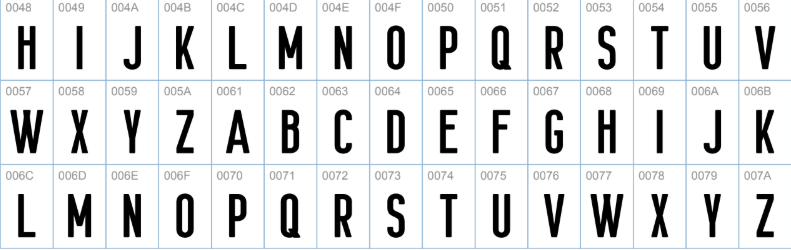
Essa mudança de fornecedor impacta drasticamente a identidade visual do kit. Saem as fontes clássicas e serifadas, entra uma tipografia moderna e agressiva. Neste post, você baixa a fonte oficial exata desta nova fase, pronta para estampar seus projetos.
- Conteúdo: Alfabeto completo (Caixa Alta) e numeração oficial da temporada 26.
Estilo Visual da Tipografia
A Puma é conhecida por romper padrões, e a fonte do Fluminense para 2026 reflete isso. A marca alemã implementou uma tipografia de estilo industrial e geométrico, alinhada com seus templates globais de “futebol de rua” e performance.
Os números são robustos, com espessura constante e cortes angulares que facilitam a leitura rápida. É um visual que moderniza a camisa listrada, criando um contraste interessante entre a tradição das cores (Verde, Branco e Grená) e a modernidade da fonte. Ideal para quem busca um visual de “velocidade” e inovação nas estampas.